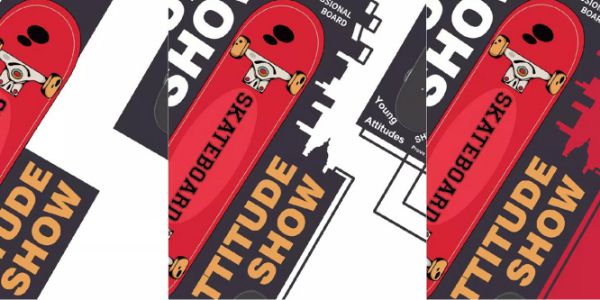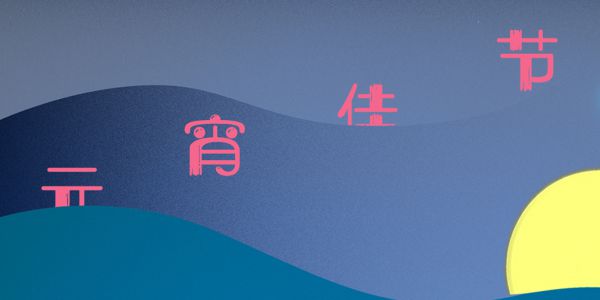
分享很火的AI设计,每一个都很实用
今天的技巧依然是来自台湾设计师施博瀚分享的 Adobe illustrator 学习教程,因为看到更新了,所以我整理了几个分享给大家。
製作
几何消隐效果
1)使用剪刀工具切断封闭的路径;
2)将笔画套用渐层色并选择「沿笔画套用渐层」;
3)加粗笔画宽度延伸至中心点;完成。
製作
隐没效果
1)输入文字并按滑鼠右键建立外框;
2)填入渐层色(注意!黑色的色标不透明度请设为0);
3)使用效果→模糊→高斯模糊;
4)设定模糊半径,按下确定;
5)使用效果→像素→网线铜版;
6)类型使用「细点」,按下确定;完成。
製作
透视扩散效果
1)排列好你要的图形并将其群组;
2)複製一份并以中心为基准缩小,更改为与背景相同的颜色、将其移至下层;
3)进入渐变工具视窗,将间距设为「指定距离」、距离数值设到极小;
4)选取这两个群组使用物件→渐变→製作;完成。
快速
绘製彩球
1)使用椭圆形工具拉出圆形;
2)使用剪刀工具,点击两端点将圆形切成半;
3)选取其中一半,使用物件→路径→反转路径方向;
4)先双击渐变工具打开视窗,间距使用「指定阶数」、设定想要的数量、按下确定;
5)选取全部图形,使用物件→渐变→製作;完成。
製作
万圣节字样效果
诡谲文字效果:
1)输入文字,使用效果→扭曲与变形→缩拢与膨胀;
2)使用「负值」,按下确定;完成。
蜘蛛网作法:
1)使用多边形工具绘製多个同心的八边形;
2)选取所有图形使用效果→扭曲与变形→缩拢与膨胀;
3)使用「负值」,按下确定,再加上对角直线;完成。
製作
具东方气质的标准字
1)使用文字工具输入文字,并把字拉宽;
2)使用效果→弯曲→拱形,微微调高弯曲数值,按下确定;完成。